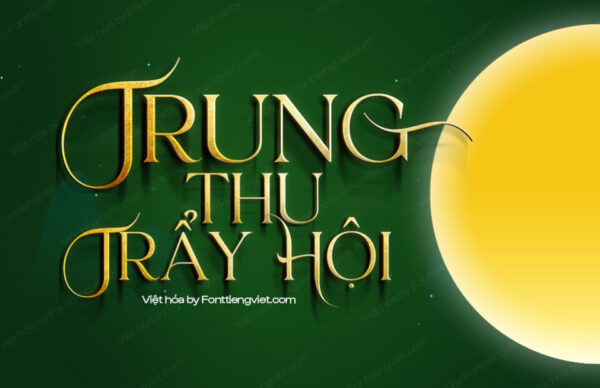
1FTV VIP Mosseta là font chữ có chân (serif) mang vẻ đẹp cổ điển pha lẫn hiện đại, được Việt hóa hoàn chỉnh với bộ glyphs phong phú giúp thể hiện tinh tế mọi thông điệp thiết kế. Đây là lựa chọn lý tưởng cho những ai muốn tạo nên sự sang trọng, trau chuốt trong từng chi tiết.
Vẻ đẹp cổ điển – Sang trọng – Đầy sáng tạo
Với đường nét thanh thoát, uốn lượn tinh tế và độ tương phản giữa nét đậm – nét mảnh, Mosseta dễ dàng tạo nên sự nổi bật trong các thiết kế như:
Thiệp cưới, thiệp chúc mừng cao cấp
Banner Tết, ấn phẩm mừng xuân
Poster sự kiện, thiệp mời sang trọng
Trang bìa sách, tạp chí nghệ thuật
Bộ Glyphs phong phú – Linh hoạt sáng tạo
Điểm mạnh nổi bật của 1FTV VIP Mosseta là hệ thống glyphs đa dạng – bao gồm các ký tự thay thế, ký hiệu trang trí, giúp bạn thỏa sức sáng tạo và cá nhân hóa trong từng thiết kế.
Việt hóa đầy đủ – Chuẩn tiếng Việt
Font đã được Việt hóa chỉn chu, hỗ trợ đầy đủ các dấu tiếng Việt, giữ nguyên vẻ đẹp thiết kế gốc mà vẫn phù hợp với ngôn ngữ bản địa, từ đó mang lại trải nghiệm thẩm mỹ trọn vẹn.
Font Việt hóa 1FTV VIP Mosseta – Font chữ có chân tuyệt đẹp cho thiệp sang trọng và banner Tết